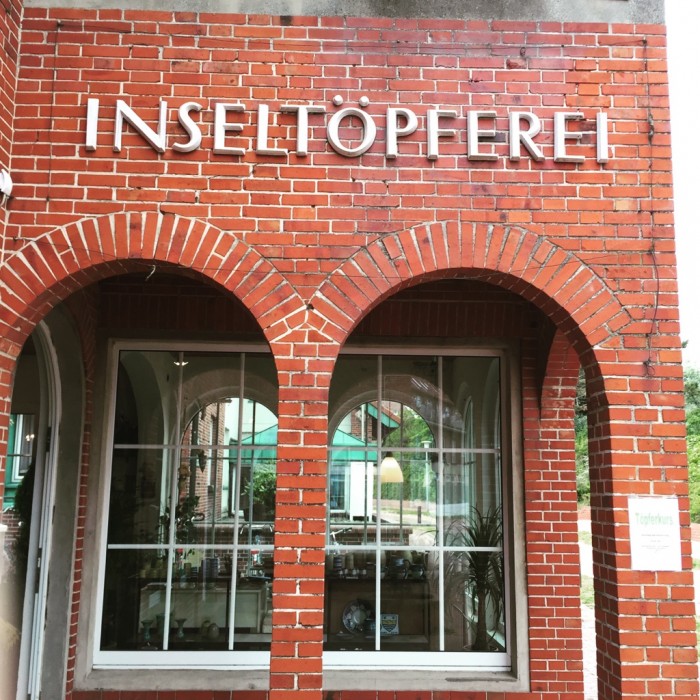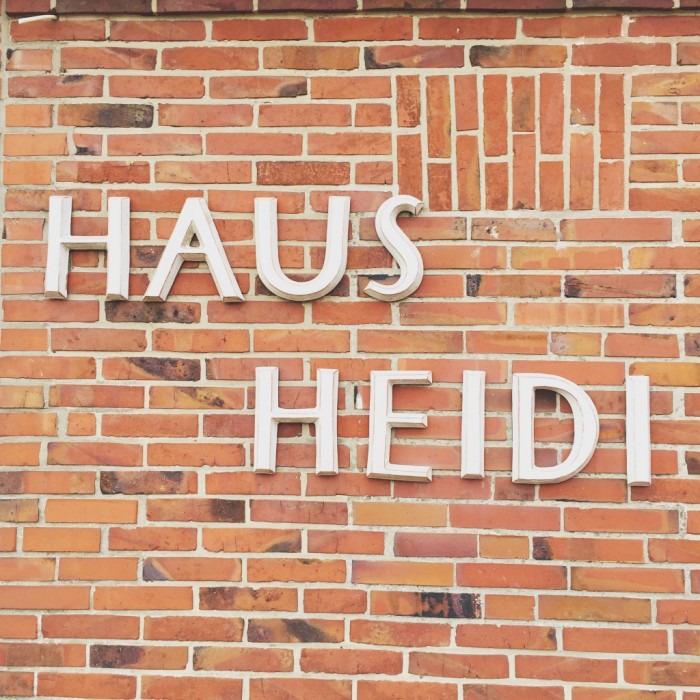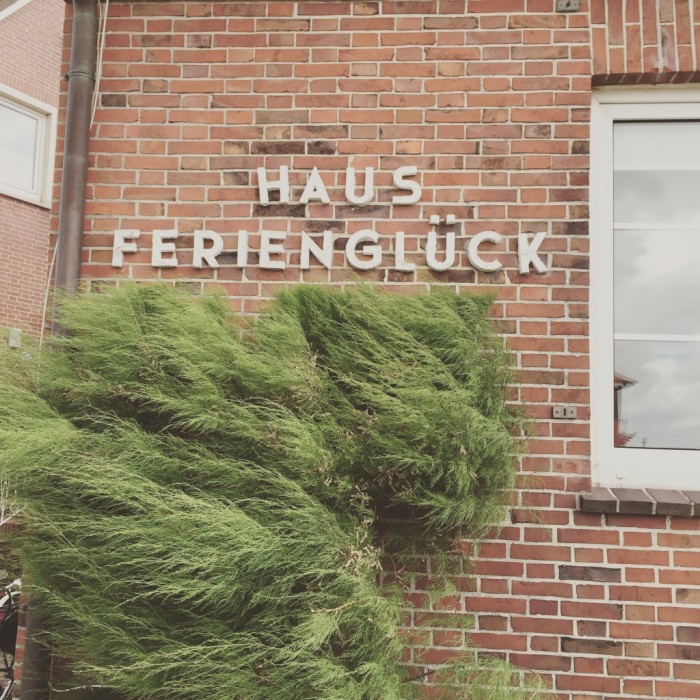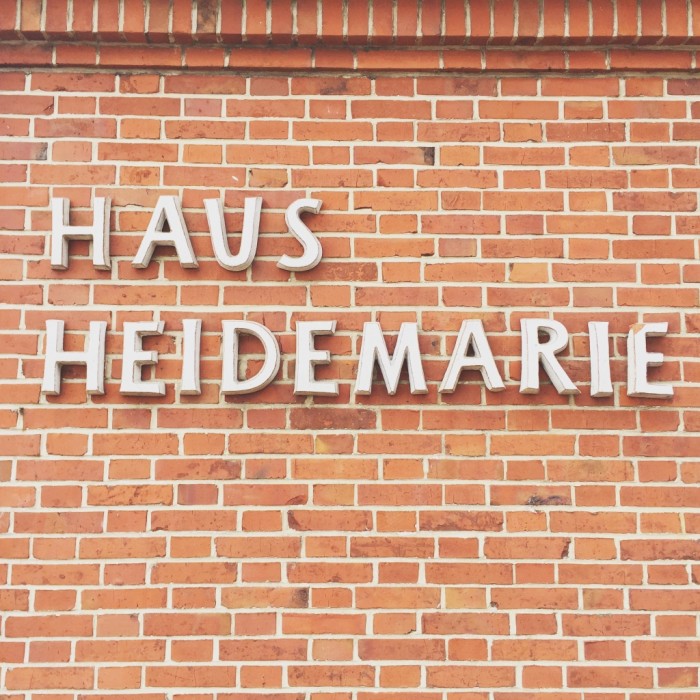
Suche Schrift wie auf Häusern an der Nordsee aus den 50er/60er Jahren
wir haben ein Haus, Baujahr 1961 und suchen einen Schrifttyp für unser Namensschild an der Tür, der zu dieser Stilepoche passt.
Uns gefallen Schriftzüge von Häuser aus dieser Zeit, die Fotos stammen aus Juist.
Wir suchen nur Großbuchstaben und gerne eine klare Schrift, die wie auf den Fotos zum Teil dickere Linien hat in der Vertikalen...
Hat jemand eine Idee, was wir von dem Graveur verlangen sollen?
Ich bin mir nicht sicher, ob die abgebildeten Schriften bzw. Vorlagen dazu unbedingt in der oben genannten Zeit entanden sind.
Meine Assoziationen zu ähnlichen Schriften:
1) Stone Sans
2) Post Antiqua
4) Oskar, Remo, Neutraface
Bei der Inseltöpferei dachte ich auch als erstes an die Optima. Es ginge aber auch sowas wie Albertus oder Clearface:
Generell könnte man unter den Stichworten flare serif oder tapered suchen.
Da findet man dann sowas:
Als mir die Infini von Sandrine Nugue gerade im Newsletter von I love typography auf den Bildschirm kam, musste ich an diese Anfrage danken. Vielleicht passt die Schrift?! Sie kommt im freien Download (CC BY-ND) mit drei Schnitten (Roman, Italic, Bold) und einem Piktogramm-Font.
Haus Ferienglück ist eine geometrische Grotesk im Stil der 1920er aus Deutschland. Ich wühle mich mal durch meine Unterlagen. Das liegt bei mir im Verzeichnis. .../font_dvd/collect/Grotesk/Geometric/Retro
So, ich wühle mich da einfach durch und werfe die rohen Häppchen vor das gierige Publikum.
Typeface:    Montserrat
Designer:    Julieta Ulanovsky
Year:        2011 (?)
Edelsans von Jakob Runge 2009, frei für nicht-kommerzielle Anwendungen ...
Typeface:    Lato
Designer:    Łukasz Dziedzic
Year:        2010-2014
Typeface:   Ministry
Designer:   Rian Hughes
Year:          2005
Publisher:  Device
Nexa von Fontfabrik, Light & Bold gibt es zum freien Herunterladen:
Nevis Gras, Freefont(?) ohne Umlaute und scharf-s ...
Typeface:  DTL Nobel
Typeface:    Relay
Designer:    Cyrus Highsmith
Year:        2001
Publisher:    Font Bureau